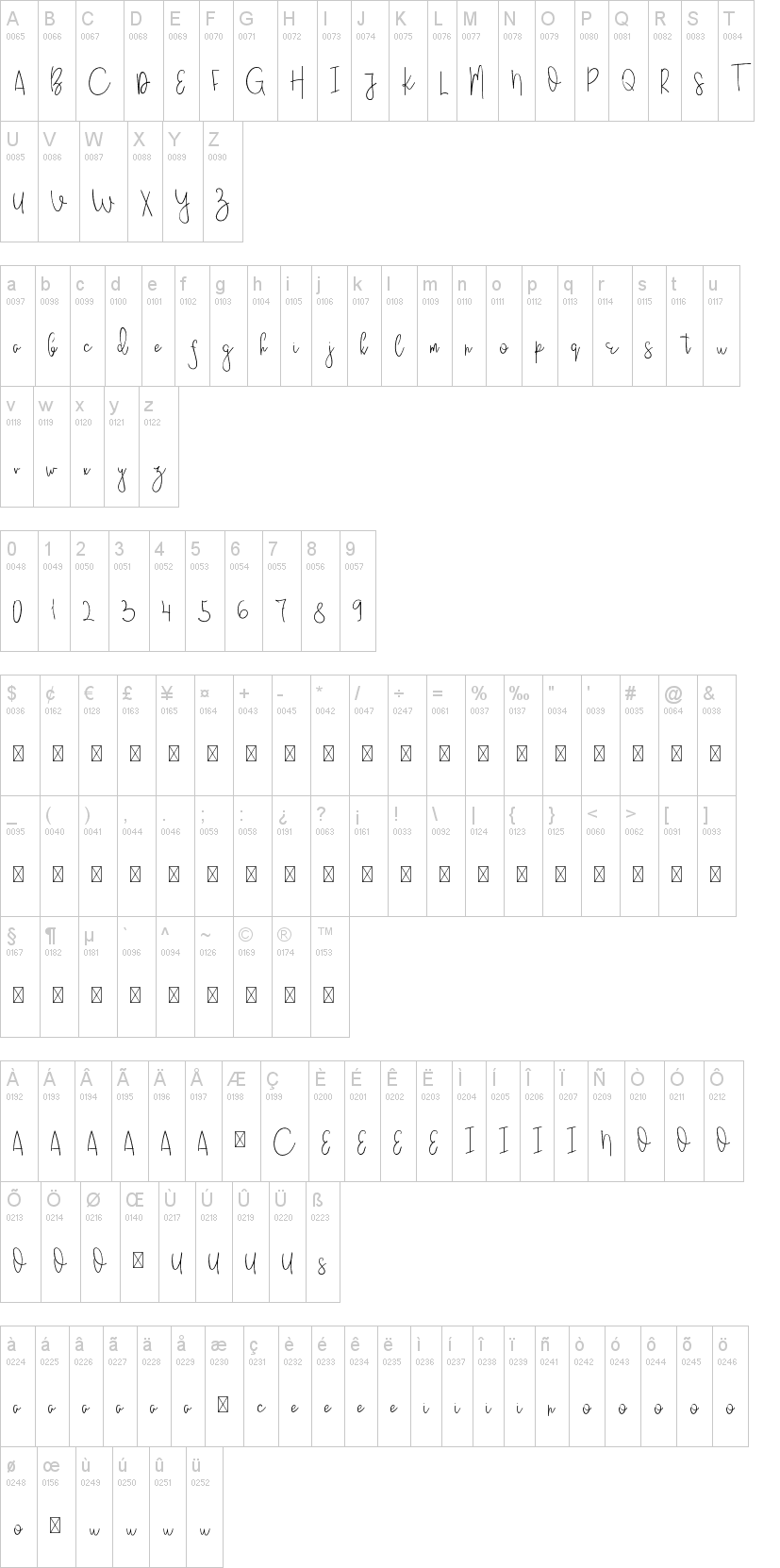
Just Because是一款简洁明了的行书字体,由英国著名设计师Paula Nazal设计,可以让你的文字更加精致而又不失简洁。它的字体线条细腻,给人一种清新的感觉,还有一些细微的变化,使它看起来更加活泼。Just Because字体适用于广告、报纸、书籍、海报、标志等各种印刷品,具有优雅、简洁的特点,可以给视觉效果增添活力。内容介绍
Just Because是一款非常不错的手写艺术字体,具有很好的视觉感,适合于文化类的宣传设计、商业类品牌的广告和产品包装设计以及个性化文字排版等较多场景。